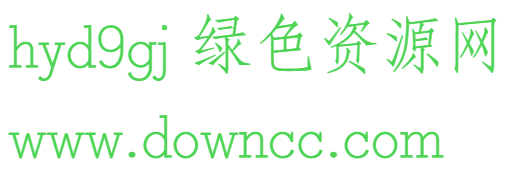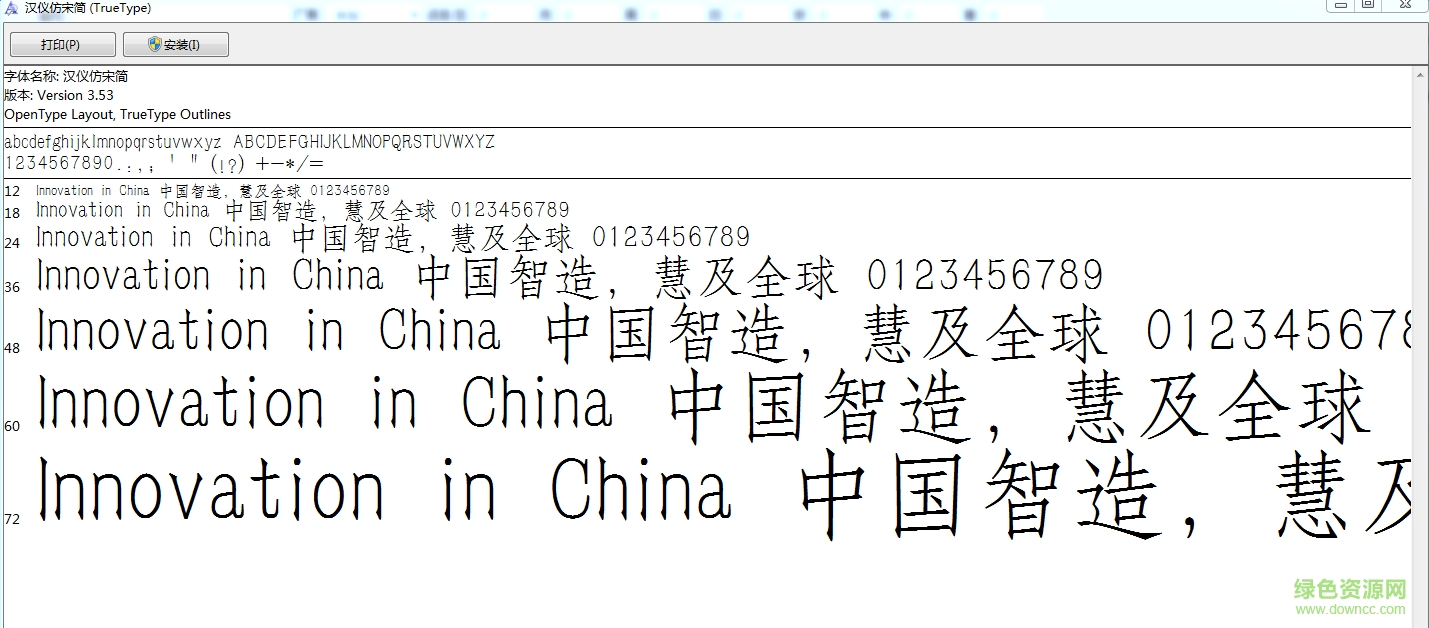
hyd9gj 0325字體是一款結(jié)構(gòu)錯落有序的漢儀仿宋字體,筆畫清晰字形干凈,適合排版印刷、報刊正文、包裝設(shè)計等方面或是用作廣告字體也可以,有需要者快來綠色資源網(wǎng)下載吧!
仿宋是印刷字體的一種,仿照宋版書上所刻的字體,筆畫粗細(xì)均勻,有長、方、扁三體,也叫仿宋體,仿宋字。仿宋體是仿照宋版書的字體演變而來的,但仿宋的結(jié)構(gòu)特征決定了它必須有一定的傾斜。
仿宋是主要的中文字體之一,但是它的使用頻率并沒有宋體、楷體高,而其實(shí)我們在電腦上面看到的仿宋是字體設(shè)計者根據(jù)古籍作品加工的,刪去了一些細(xì)節(jié),使得字體更加平滑,但是卻失去了一些字體原型的風(fēng)韻。